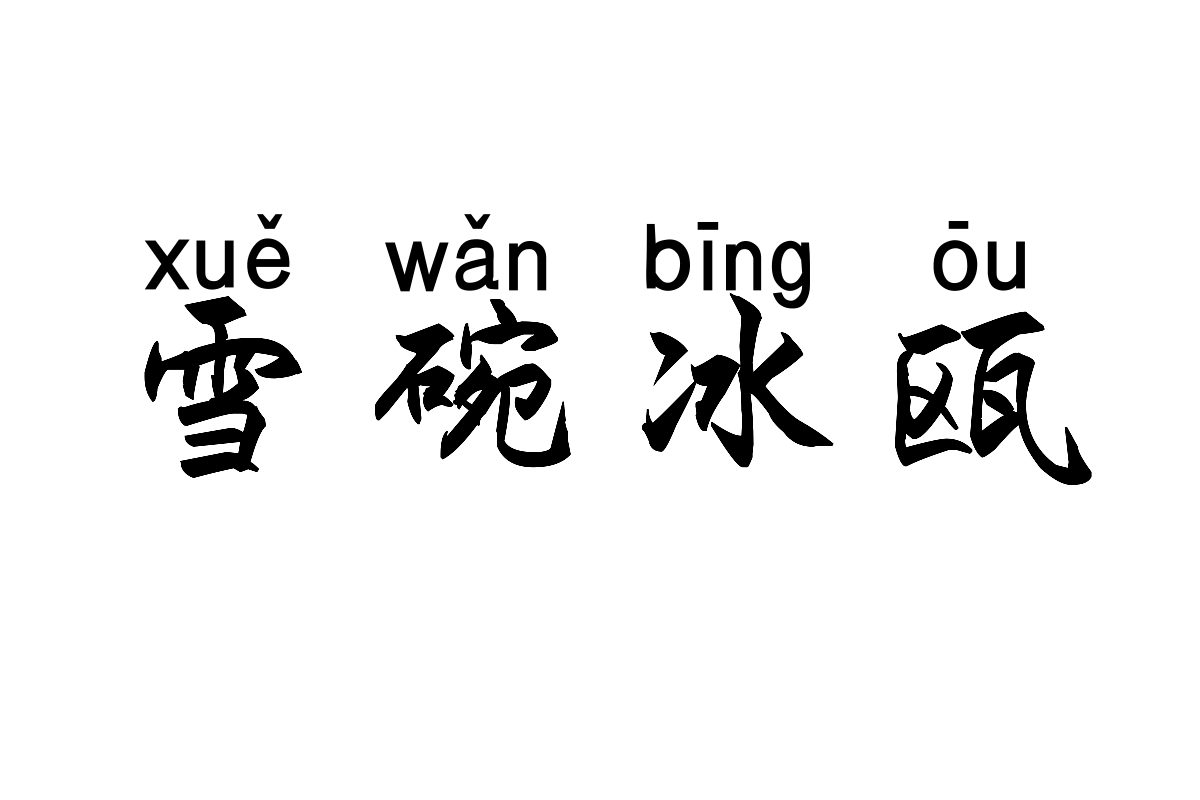
米开飘逸行楷拼音体是一款具有独特风格的字体,它采用了现代的设计元素,结合了传统书法的韵味,创造出了一种既简洁又富有艺术感的字体。该字体的特点是笔画流畅,字形优美,线条粗细适中,给人一种优雅、大方的感觉。
米开飘逸行楷拼音体的字形结构紧凑,每个字都经过精心设计,使得整体看起来非常和谐。它的笔画粗细变化丰富,既有粗犷的线条,又有细腻的笔触,使得整个字体既有力度感,又不失柔美。
该字体还特别注重细节的处理,无论是笔画的起止点还是字与字之间的间距,都经过精心计算,使得整体看起来非常协调。此外,它还采用了一些特殊的设计元素,如装饰性的图案或符号,使得整体看起来更加生动有趣。
总的来说,米开飘逸行楷拼音体是一款集美观、实用于一体的字体,无论是用于印刷品、广告还是其他需要展示文字的场合,都能展现出其独特的魅力。